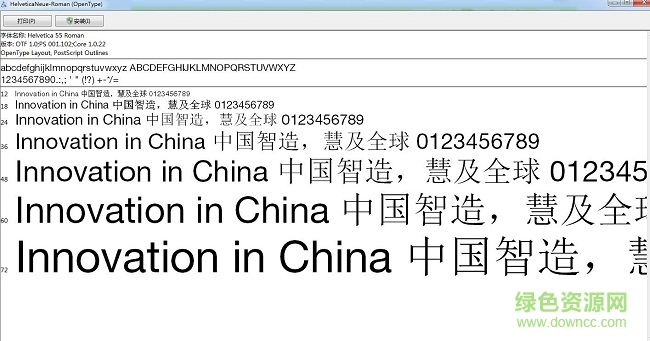
helveticaneueroman字體
helveticaneue roman字體是一款常常用于商業(yè)設(shè)計的英文標(biāo)準(zhǔn)字體,細(xì)節(jié)飽滿,便于識別,整體風(fēng)格和諧一致,應(yīng)用范圍廣,實用性強,需要的朋友快來綠色資源網(wǎng)下載吧!
helveticaneueroman字體